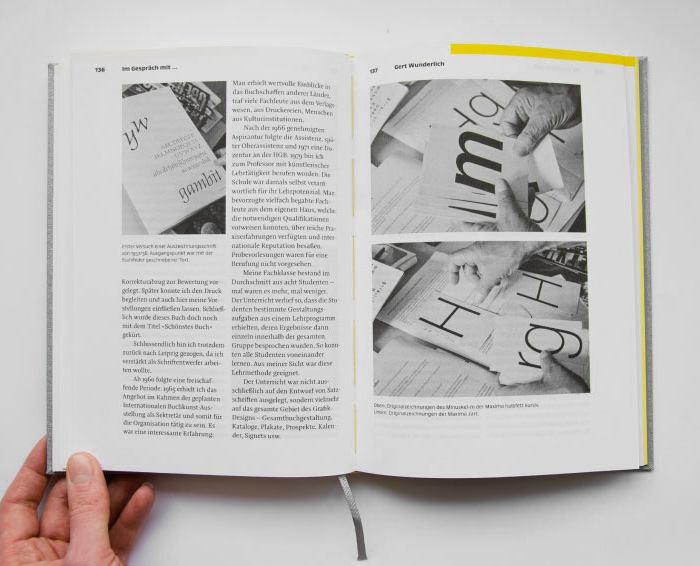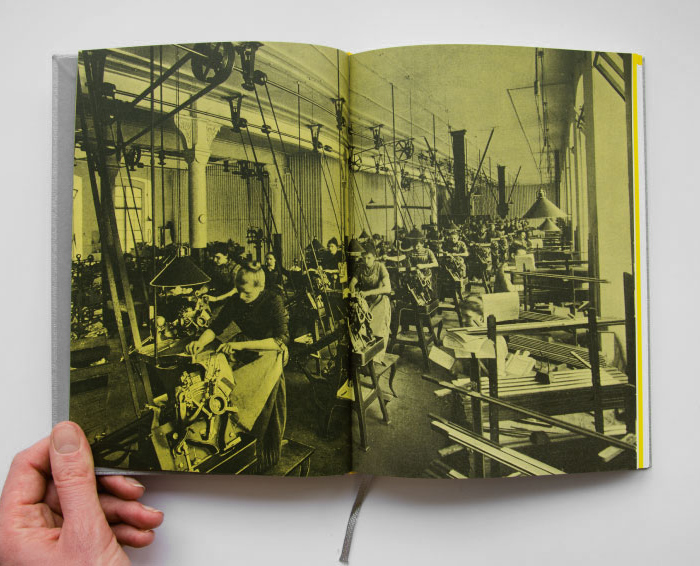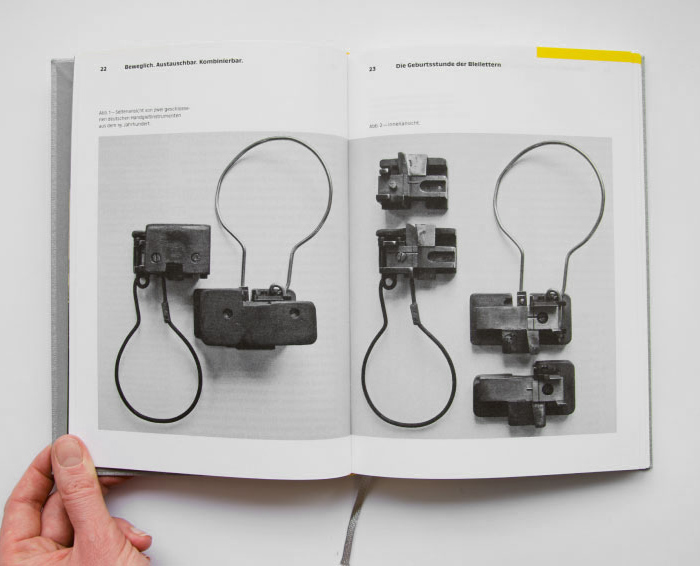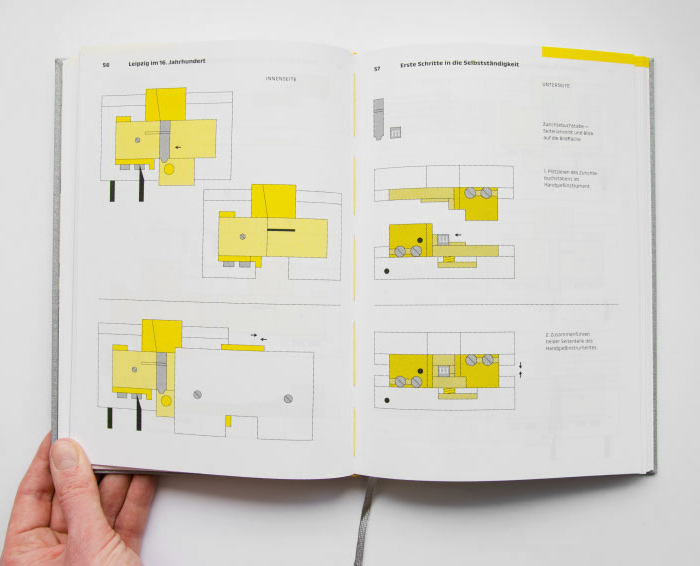
Die Zeit, in der die Letternproduktion mit einem tonnenschweren Material- und enormen Zeitaufwand verbunden war und Buchstaben in Form eines dreidimensionalen Körpers greifbar, messbar und nach Gewicht bestimmbar waren, fand mit den technischen Entwicklungen des vergangenen Jahrhunderts ihr Ende. Obwohl Formensprache und -logik auf Jahrhunderte tradierten Gesetzmäßigkeiten beruhen, ist die Schriftproduktion heute vom ursprünglichen Handwerk weit abgerückt: Gestaltung sowie Herstellung von Schrift erfolgen am Computer mittels Software.
Lediglich die Bezeichnung der Schriftverlage als Foundrys (also Gießereien) schafft eine Verbindung in die Bleisatzzeit. Relikte dieser Ära findet man heute nur noch in musealer Umgebung, speziellen Ausbildungsstätten oder kleinen Druckereien, die für Liebhaber des Vergangenen Drucksachen im Bleisatz realisieren.
In ihrem Buch »Leipziger Kegel«, das als Abschlussarbeit in der Schriftklasse an der Hochschule für Grafik und Buchkunst Leipzig entstand, wirft Monique Dickmanns einen Blick zurück. Der erste Teil des Buches geht der Frage nach, wie sich die Schriftgießereien entwickelten. Ausgehend von Leipzig, welche lange Zeit als die Stadt des Buches weltweites Ansehen genoss, findet eine chronologische Aufarbeitung der Stadtgeschichte aus Sicht eines Industriezweiges statt, der als Kernstück der buchherstellenden Industrie hinter den weiterführenden Produktionszweigen oft im Hintergrund blieb.
Dabei beginnt die Betrachtung mit der Erfindung des Buchdrucks in der Mitte des 15. Jahrhunderts und dessen Aufkommen in Leipzig durch die Frühdrucker, erstreckt sich über die Entstehung der ersten Gießereien, ihrer Emanzipation zu selbstständigen Unternehmen sowie deren Blütezeit und endet mit der Einstellung der Bleiletternproduktion im 20. Jahrhundert.
- Beweglich. Austauschbar. Kombinierbar. – Die Geburtsstunde der Bleilettern
- Leipzig im 15. Jahrhundert – Auf den Spuren früher Drucktypen
- Leipzig im 16. Jahrhundert – Erste Schritte in die Selbstständigkeit
- Leipzig im 17. Jahrhundert – Anton Janson und die eigenständige Schriftgießerei
- Leipzig im 18. Jahrhundert – Normierung im Schriftguss
- Leizpig im 19. Jahrhundert – Vom Blei zum digitalen Abbild
- Ausblick – Schriftschaffen heute
Den zweiten Teil des Buches bilden Gespräche mit fünf Zeitzeugen, welche für die letzte kommerziell tätige Leipziger Schriftgießerei arbeiteten. Neben den Schriftkünstlern Hildegard Korger und Gert Wunderlich, deren Schriften beim VEB Typoart Dresden realisiert wurden, kommen ebenfalls ein Galvanoplastiker und Justierer, ein Stempelschneider sowie ein Schriftgießer zu Wort, berichten unter anderem von ihrem Arbeitsalltag und erinnern sich an den Moment der Schließung des Unternehmens.
Das Buch ist reich bebildert und wartet mit interessanten fotografischen Fundstücken aus der Leipziger Schriftproduktion auf. Leider ist die Qualität der Abbildungen nicht immer optimal.
Gesetzt wurde das Buch übrigens aus der Schrift Mingo der Autorin sowie der Zentral ihres Geschäftspartners Peter Mohr.